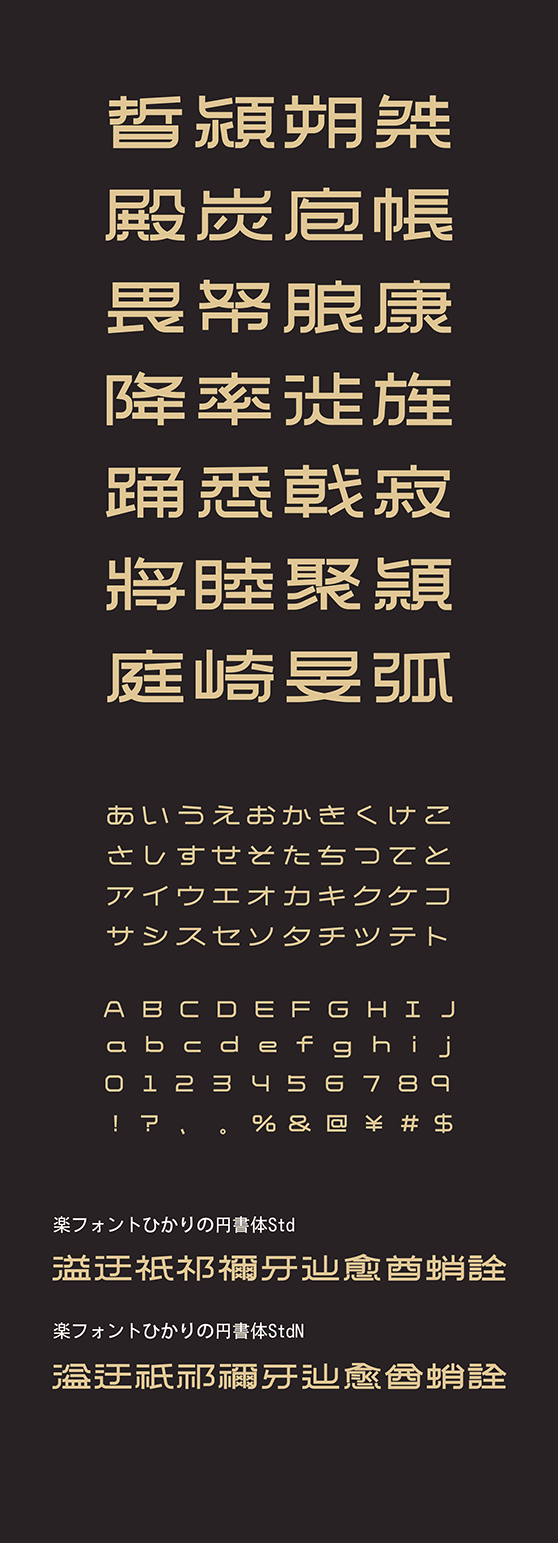
楽フォント
ひかりの円書体 (ひかりのえんしょたい Std・StdN同梱)
HikarinoenshotaiStd, HikarinoenshotaiStdN
このフォントは、柔らかな丸みと整った幾何構造により、やさしさと見やすさを両立した現代的な表情を持ちます。なめらかな筆画が読みやすさを高め、落ち着いた印象を生み出します。UI 表示やブランドツール、教育・生活分など、温かさと機能性を求める幅広いデザインに最適です。